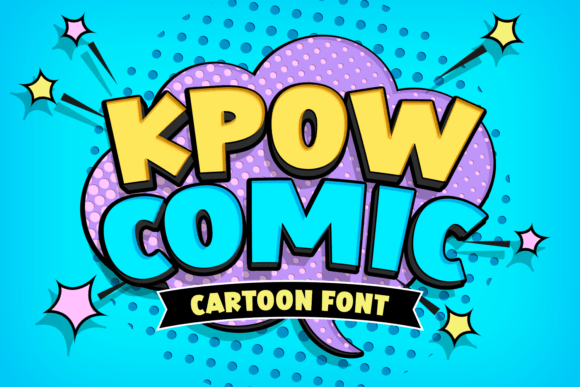
Kpow Comic Font
Kpow Comic Font – خط إبداعي مستوحى من عالم الكوميكس!
اجعل تصميماتك تنبض بالحياة مع Kpow Comic Font، الخط المثالي لإضافة لمسة من المرح، الديناميكية، والطابع الكرتوني إلى مشاريعك. يتميز هذا الخط بحروفه الجريئة والمنحنية التي تجذب الانتباه، مما يجعله مثاليًا لعناوين الكوميكس، تصميمات الألعاب، الشعارات، الملصقات، والمحتوى الإبداعي.
✨ مميزات الخط:
✔ تصميم احترافي مستوحى من أسلوب الكوميكس الكلاسيكي
✔ يدعم الأحرف الكبيرة والصغيرة لمزيد من التنوع
✔ مثالي للعناوين، الشعارات، والمواد التسويقية الجذابة
أضف لمسة مليئة بالحركة والطاقة إلى تصاميمك مع Kpow Comic Font! ????